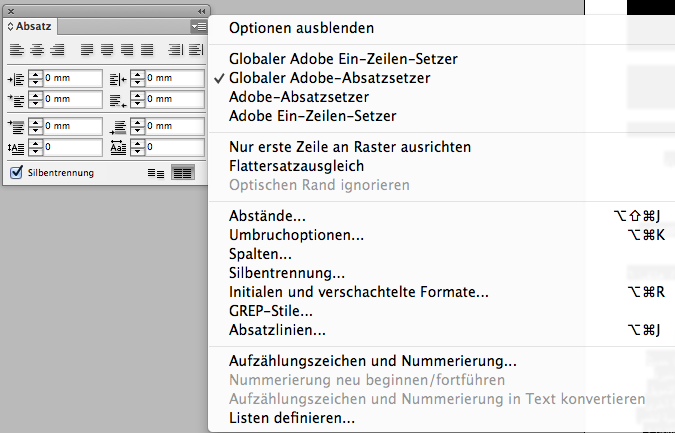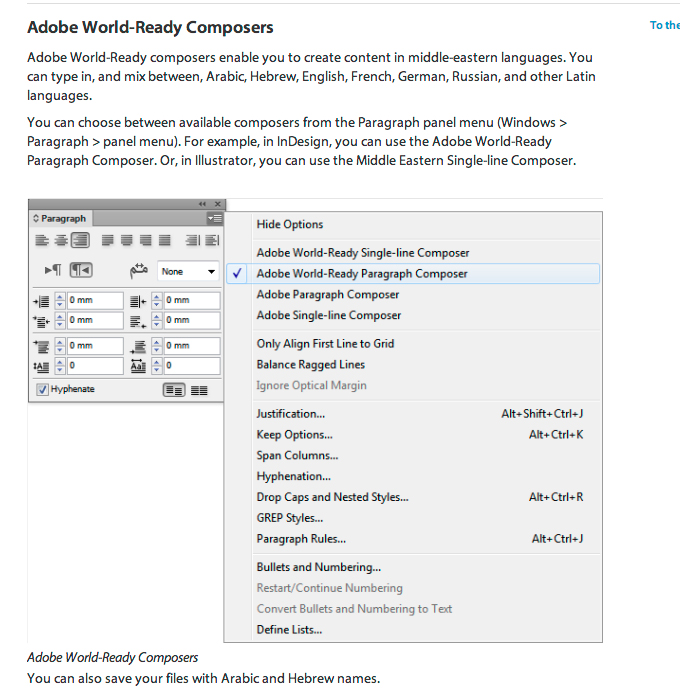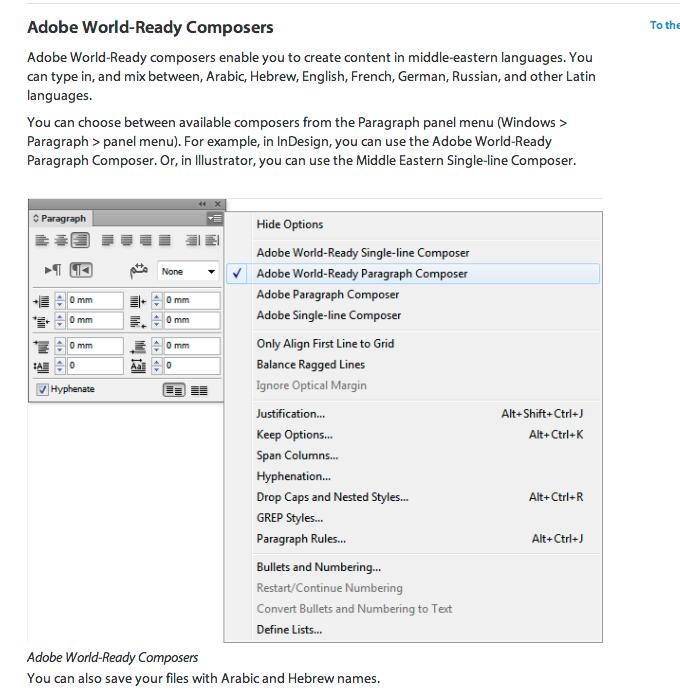
Broschüre in arabischer Schrift
ich habe eine Anfrage bekommen, eine Broschüre in arabischer Schrift zu layouten. Da ich das noch nie gemacht habe, wollte ich wissen, was es dabei zu beachten gibt, z.B.:
1. Gibt es eine Standard Schrift?
2. Wie mach ich das mit der Tastatur? Woher weiß ich welcher Buchstabe dem Arabischen entspricht?
3. Wie hat es mit dem Layouten geklappt, wenn man kein Arabisch lesen kann?
Das ist nich trivial, da du erstmal rechts-nach-links-Unterstützung brauchst und sich außerdem die Buchstaben je nach Stellung im Wort ändern. Mit welcher Software arbeitest du? Das Standard-InDesign etwa kann das nicht. Mann braucht dafür die Version InDesign Middle East.
eine sprache zu setzten, die man selbst nicht spricht und dann
noch nichtmal lesen kann würde ich mir nicht zutrauen. vielleicht mal
ein/zwei zeilen aber niemals eine komplette broschüre.
Ich hab mal ne zweisprachige Broschüre gesetzt (Arabisch-Englisch) auf einem rechner von nem Araber. Der hatte ein Zusatztool für Quark, das die Schrift korrekt gesetzt hat. Die Arabische Schrift ist nicht ohne, während des Tippens haben sich permanent Ligaturen gebildet und mit jedem neuen Buchstaben auch wieder verändert. Die Tastatur ist in vielen Ebenen belegt und ich hatte überhaupt keine Ahnung, was ich da tat. Selbst einfache gerade Linien mit einem Punkt drauf können unter Umständen ganze Worte sein.
Ohne jemanden, der das lesen kann, was ich da setze, würde ich sowas nicht nochmal machen. Auf dem Rechner waren ungefähr genau so viele arabische Schriften, wie es Varianten von der Lucida gibt. In allen erdenklichen Anmutungen und Ausformungen. DIE arabische Schrift scheint es da nicht zu geben, wohl aber so was wie die arabische Helvetica.
Nimm den Job nur an, wenn du es irgendwie organisiert bekommst, das zu lesen. Das Quarktool ist sicher auch nicht umsonst, also muss sich der Auftrag auch rechnen.
Die "arabische Helvetica" heißt Yakout –
Sie sieht nicht nach die Helvetica aus, ist aber ebenso in der arabische Welt verbreitet wie Helvetica bei uns.
Wenn man die Helvetica World OpenType Fonts verwendet (die Lateinisch, Griechisch, Kyrillisch, Hebräisch und Arabisch drin haben), sind die arabische Glyphen die von Yakout, obwohl sie stylisch eigentlich nicht zu Helvetica passen (anders als die griechische, kyrillische und hebräische Glyphen…). http://www.linotype.com/48344/helvetica ... amily.html
Sorry to do this in English, my german reading skills are OK, but not my writing... I agree with the messages above, such a job without at least some knowledge of the language and/or the script can be a nightmare.
At least you should have the ME edition of Indesign of the equivalent product for XPress.
Interessant ist noch das Thema, wie man das Ganze druckt. Wenn ich jetzt nicht falsch denke, muss man ja jede Seite 180 Grad drehen (stehen dann auf dem Kopf) und in InDesign die Seiten von hinten an anordnen. Die letzte Seite ist die erste. Denn der Bund ist ja dann auf der rechten, statt standardmäßig auf der linken Seite …
Dieses lässt die Schrift von rechts nach links laufen und führt damit dazu, dass sich die arabischen Schriftzeichen verbinden. Außerdem noch andere Einstellungsmöglichkeiten. Auch Schriftmischungen (deutsche Wörter innerhalb eines arabische Textes) sind möglich.
Man kann auch ein arabisches Dokument ganz neu beginnen. Dann sind die Seiten in InDesign mit rechten Bund angeordnet. Vielleicht bekommt man so auch eine passende Ausgabe für den Druck … ich habe es noch nicht ganz verstanden …
Generell einmal ein paar Worte zur arabischen Schrift.
Erst einmal braucht man auf der Tastatur nicht mehr Tasten, und sie ist auch nicht wesentlich mehr belegt als unsere übliche Tastatur, nur sind eben auch die lateinischen Buchstaben abgebildet, damit man zum englischen lateinischen Tastaturlayout umschalten kann und eben bestimmte Worte in lateinischer Schrift schreiben kann.
Die arabische Schrift ist eine Buchstabenschrift genau wie unsere, nur eben mit dem Unterschied dass sie von rechts nach links geschrieben wird, dass sie keine Vokale enthält, wie auch die hebräische Schrift und das eben alle Buchstaben miteinander verbunden geschrieben werden, ähnlich einer Schreibschrift.
Dies bedeutet aber auch, dass es von jedem Buchstaben mindestens drei Versionen, in vielen Fällen jedoch auch vier Versionen gibt. Nämlich eine Version für den Anfang eines Wortes, eine Version im Inneren eines Wortes und eine Version für das Wort Ende, darüber hinaus von vielen Buchstaben die auch alleinstehend ein Wort ergeben auch eine isolierte Version. Gibt man jetzt auf der arabischen Tastatur einen Buchstaben ein, so wird zunächst die isolierte Version angezeigt, gibt man den nächsten Buchstaben ein, Dann verändert sich der erste Buchstabe in seine Anfangsform und der gerade eingegebenen Buchstaben in die jeweilige Endform. Schreibt man jetzt weiter wird der zuletzt eingegebenen Buchstaben in die mittlere Form verwandelt und der neu hinzugekommene zunächst in die Form für das Wortende gebracht. Das setzt sich sofort bis das ganze Wort geschrieben ist. Eine Sonderstellung nimmt die Zusammenstellung der Buchstaben Alef und Lem ein, Welche immer zu einer Ligatur zusammengefasst werden, ebenso gibt es eine Ligatur für den Gottesnamen Allah, für den Namen Mohammeds (sein Name werde gepriesen) sofern es sich um den Namen des Propheten und nicht um den Vornamen eines normalen Menschen handelt und ein paar weitere.. Zusätzlich gibt es dann auch einen geraden Strich, mit dem man die Wörter aus optischen Gründen noch etwas in die Länge ziehen kann, umso zu einer gleichmäßigen Zeilenlänge zu kommen.
Teilweise kann ich das nur verhindern, wenn ich Absätze reinknalle.  Aber da ich eine bestimmte Zeilenlänge füllen möchte, wirkt das ziemlich beschissen, wenn nur die halbe Zeile beschrieben ist.
Ich habe das Gefühl, dass ich nicht um die ME-Version bzw die Neuinstallation drum herum komme. Das Umstellen in der Adobe Creative Cloud hat mir ja nicht geholfen.